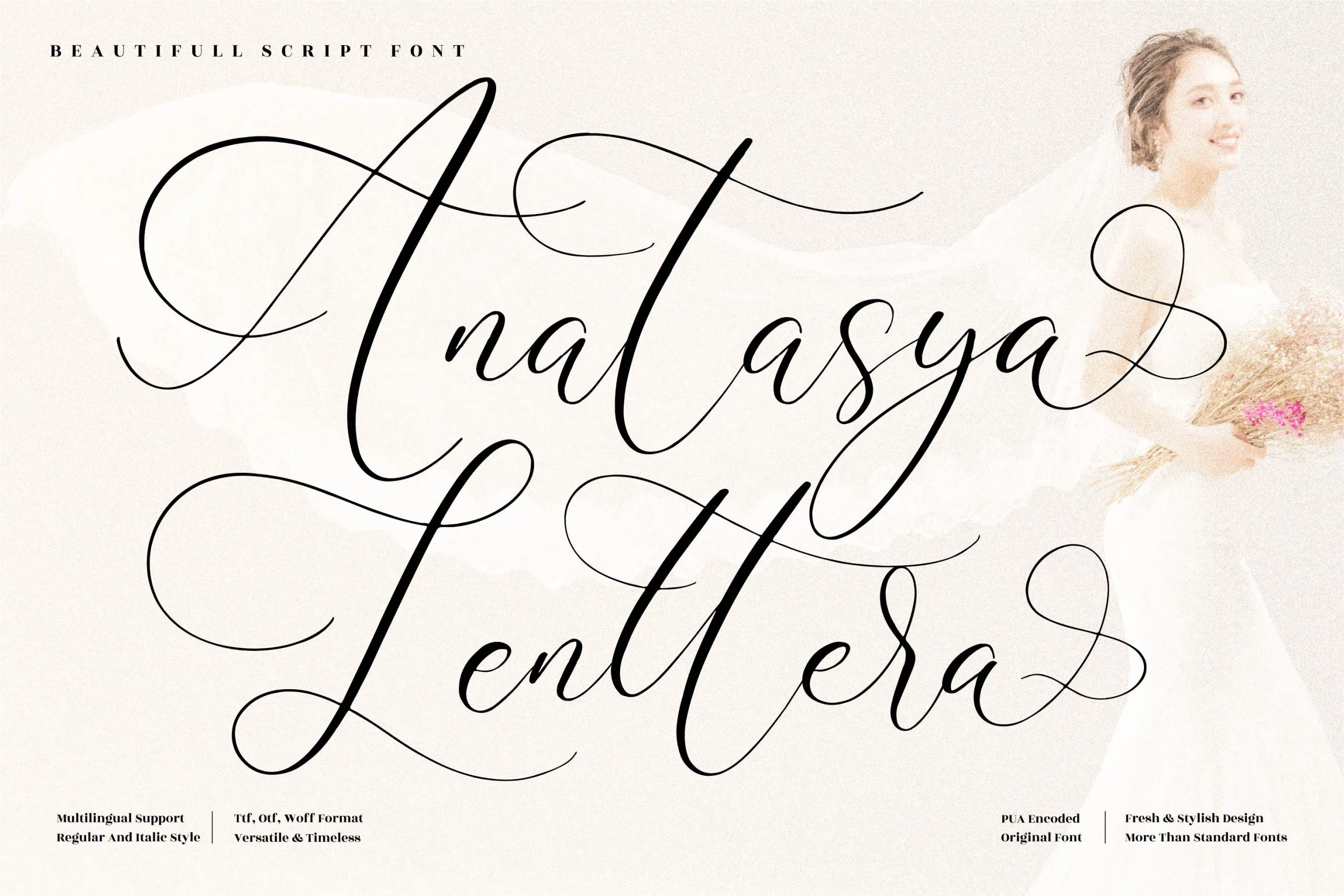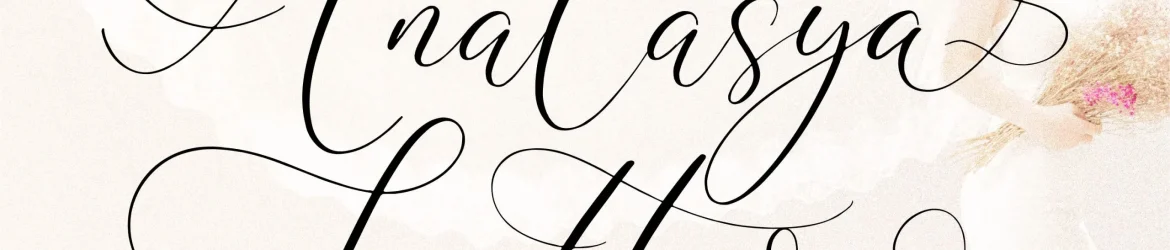
Anatasya é uma elegante tipografia de escrita romântica criada para designers que buscam um estilo cuidadosamente trabalhado e envolvente, capaz de adaptar-se a múltiplos projetos gráficos. Suas linhas fluidas e delicadas são perfeitamente adaptáveis aos mais variados usos, desde identidades corporativas e embalagens até cartões de visita e adesivos. Este é um recurso para designers que desejam dar um toque suave e aconchegante a qualquer projeto, permitindo-lhes explorar uma variedade imensa de possibilidades criativas em seu trabalho. Com sua rica disposição de detalhes, Anatasya é uma escolha ideal para aqueles projetos em que o cuidado com o sabor da escrita e o toque personalizado são essenciais.